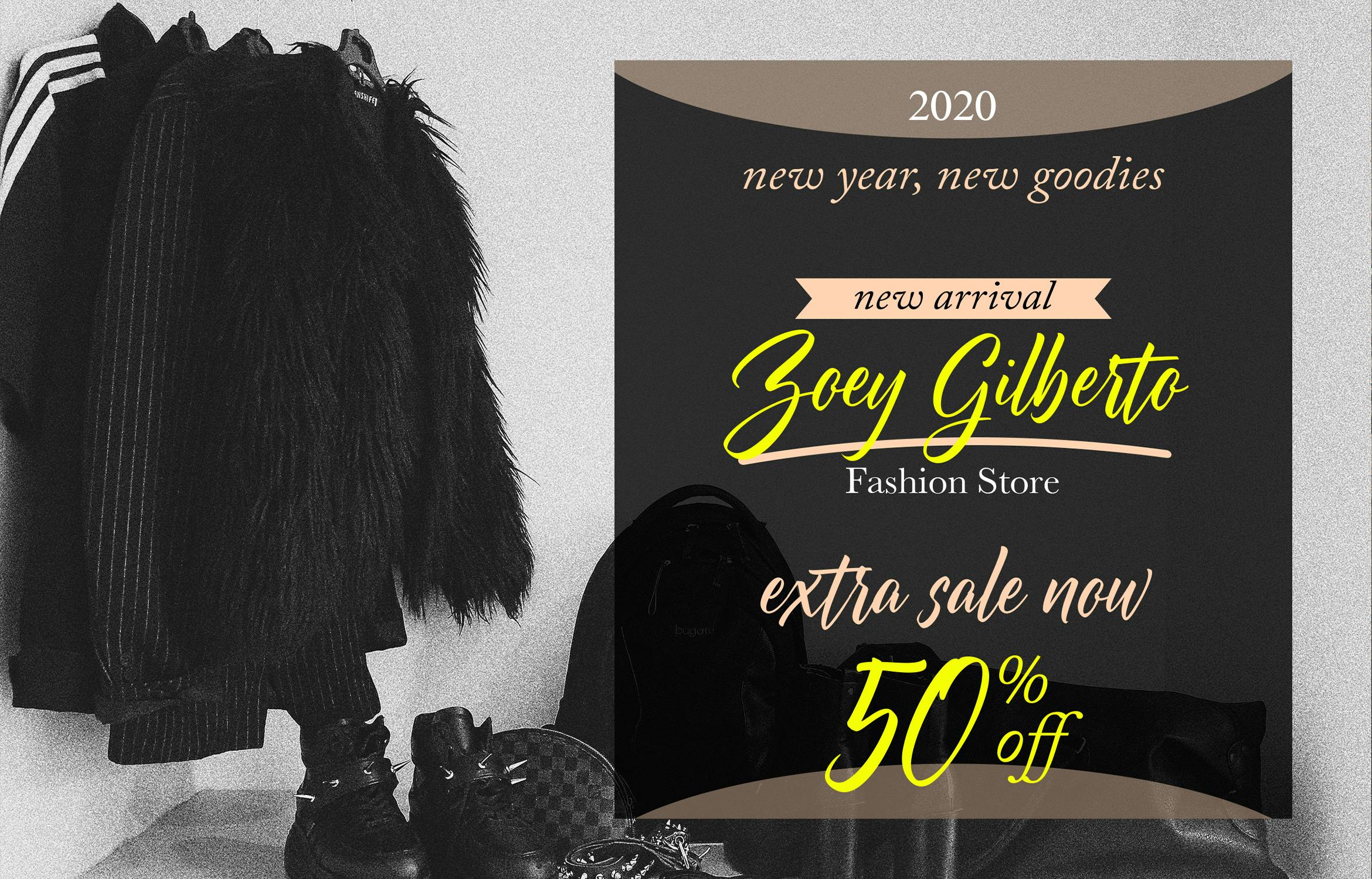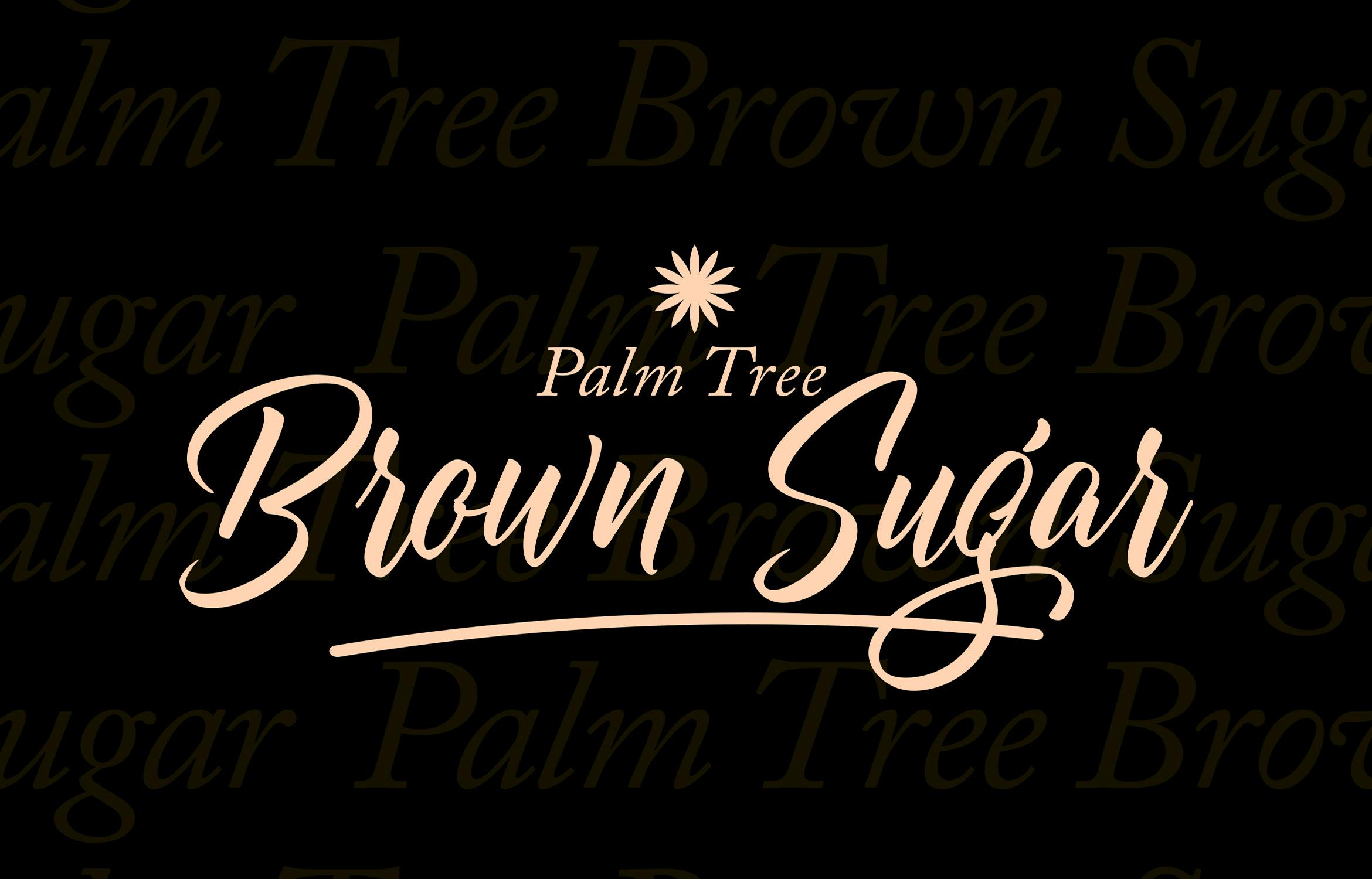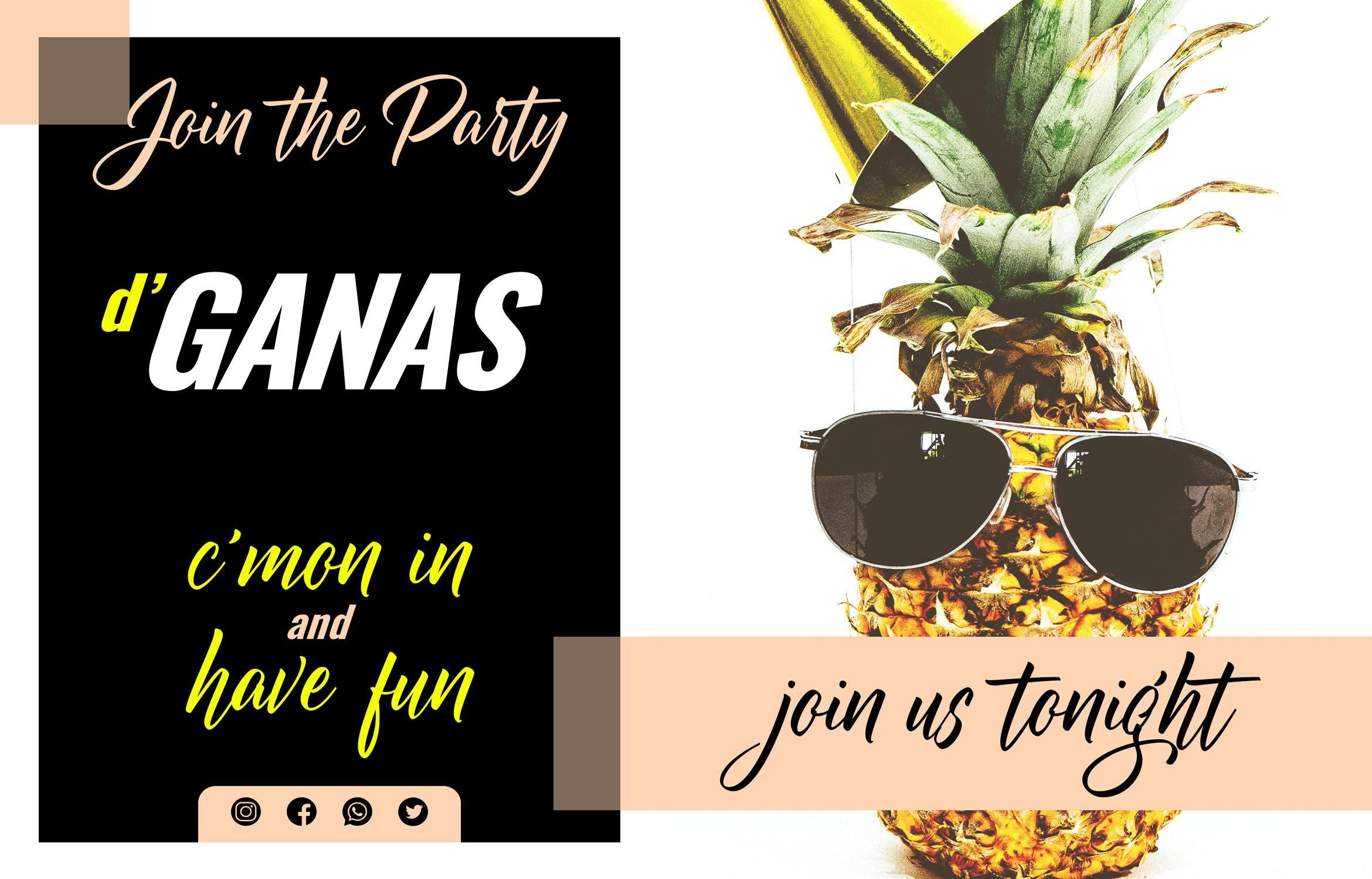
بلک وینگ | فونت اسکریپت خوشنویسی سفارشی با سبک خطاطی، بسیار زیبا برای دعوتنامهها، کارتهای تبریک، مواد برندینگ، کارتهای ویزیت، نقل قولها، پوسترها و بیشتر!
کاراکترهای جایگزین در چندین ویژگی Open Type تقسیمبندی شدهاند، مانند مجموعههای استایلیستی، جایگزینهای متنی، SWASH و Ligature. ویژگیهای Open Type را میتوان با استفاده از برنامههای Open Type مانند Adobe Illustrator، Adobe InDesign، Adobe Photoshop Corel Draw X و Microsoft Word دسترسی پیدا کرد. این فونت دارای کدگذاری PUA (فونتهای ویژه) است، به طوری که تمام کاراکترهای جایگزین به راحتی در دسترس هستند.